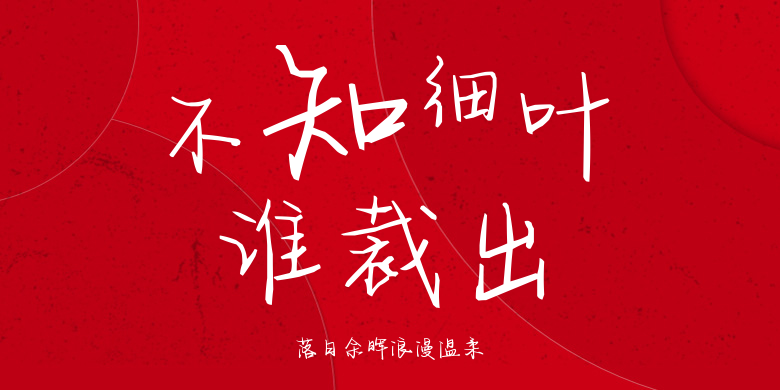
落日余晖浪漫温柔
落日余晖浪漫温柔,这款字体结构工整、笔画清晰,兼顾美观与易读性,适用于标题、正文、海报、包装、LOGO 等多种场景。字形优雅稳定,风格百搭耐看,适配日常排版与创意设计,让文字呈现更舒适、更具质感。落日余晖浪漫温柔一笔一画,皆是细节,以均衡的比例、流畅的线条打造舒适视觉体验,字形端正大气,风格简约现代。无论是商业设计、品牌宣传还是日常排版,都能轻松驾驭,让文字更有格调与力量。落日余晖浪漫温柔字体下载。